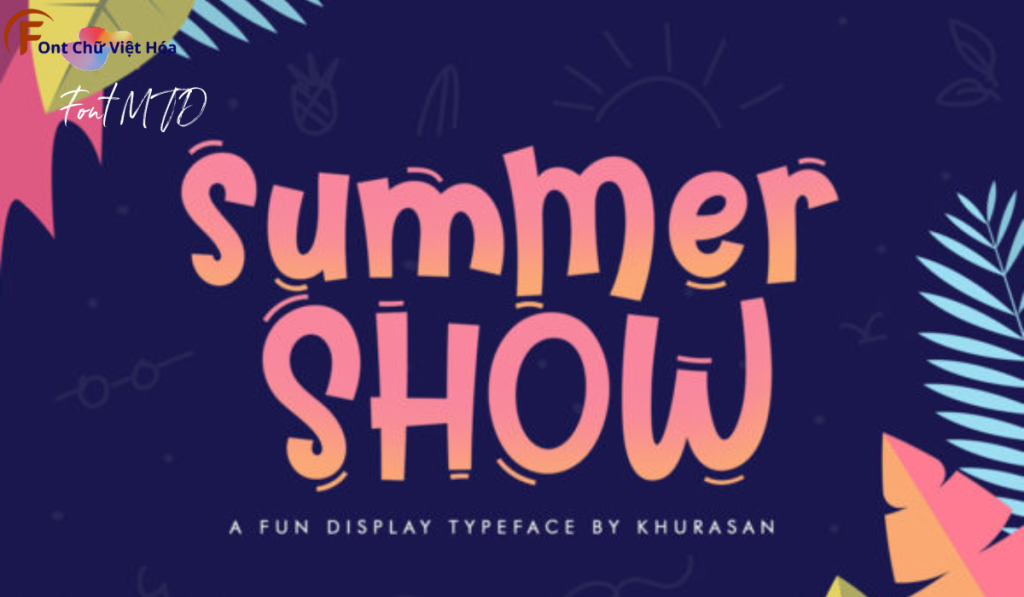
Font MTD Summer Show Việt Hóa
Font MTD Summer Show Việt Hóa, thuộc bộ font MTD, mang phong cách vui tươi và sáng tạo, phù hợp cho các dự án thiết kế như poster, logo, và bao bì sản phẩm. Với các nét chữ không chân và độ dày đều đặn, Font MTD Summer Show Việt Hóa không chỉ dễ đọc mà còn tạo cảm giác hiện đại và phá cách. Việc Việt hóa font giúp người dùng dễ dàng tích hợp vào các thiết kế tiếng Việt, mang lại sự tiện lợi và nâng cao tính thẩm mỹ.